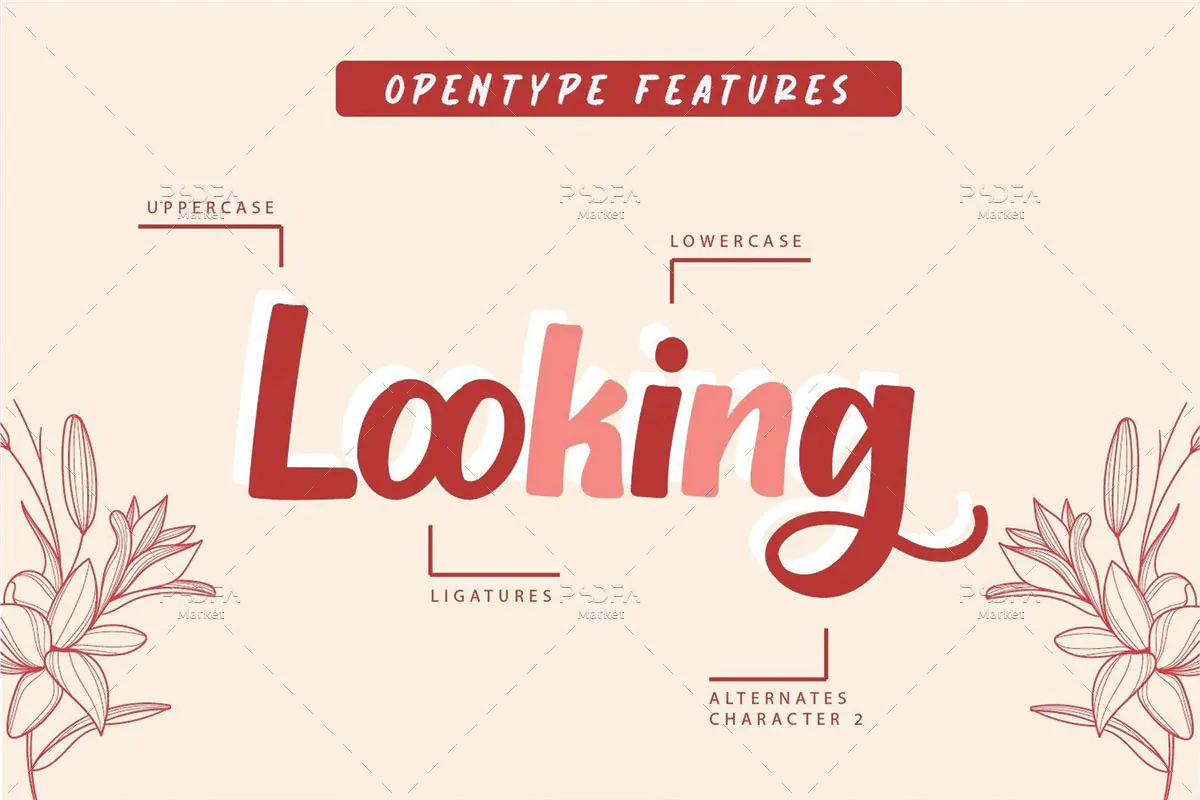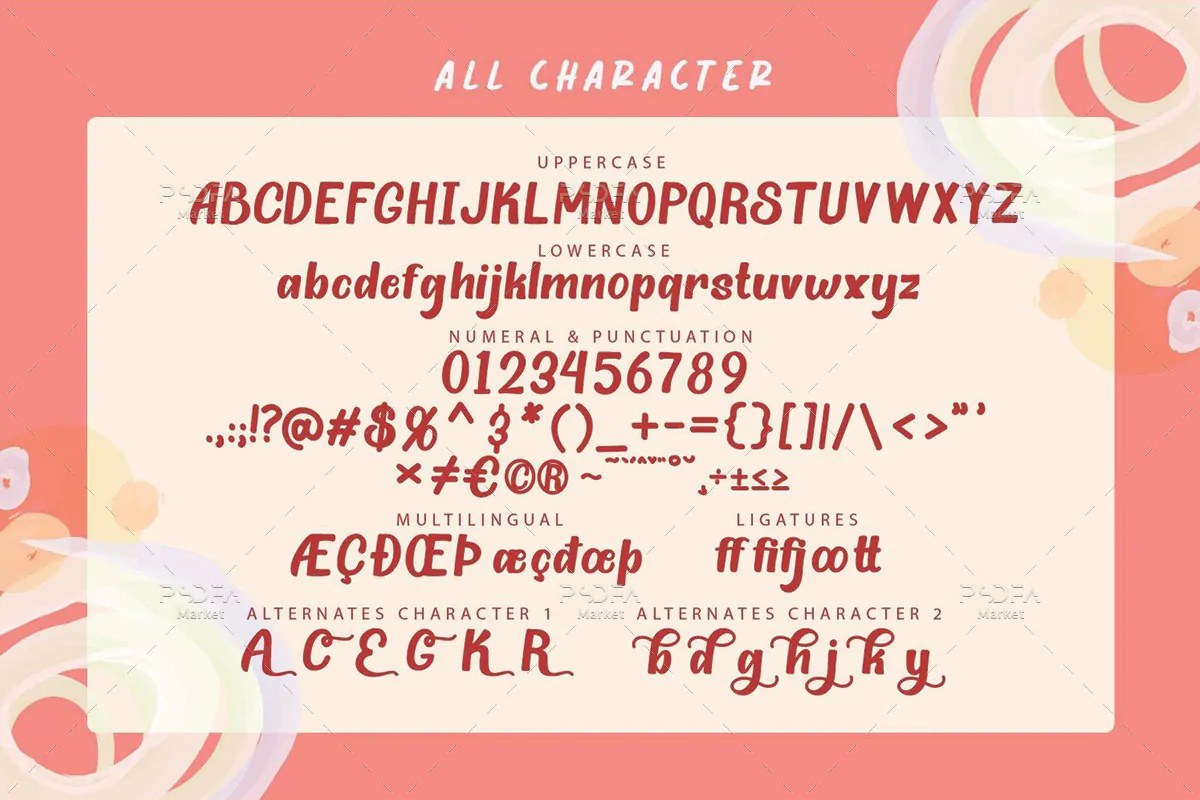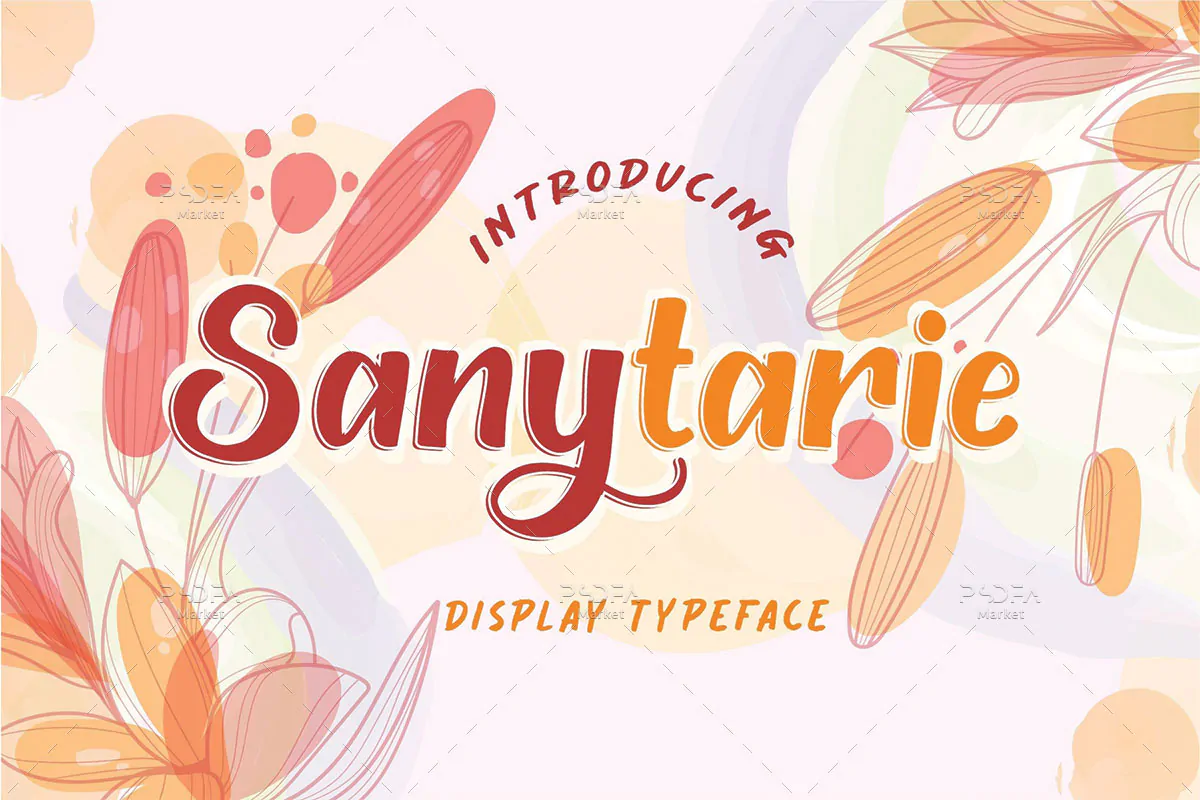
فونت نمایشی زیبا و مدرن Sanytarie
فونت نمایشی زیبا و مدرن
فونت نمایشی زیبا و مدرن Sanytarie یک قلم انگلیسی جذاب است که میتوانید از آن در طرح و پروژههای مختلف استفاده کنید. فونت Sanytarie با وزن معمولی طراحی شده است و مناسب جهت استفاده در طراحی انواع کارت تبریک، پوستر، بنر، بسته بندی محصولات، لوازم التحریر، رسانههای اجتماعی، آرایشی و بهداشتی، ظروف یکبار مصرف و … میباشد.